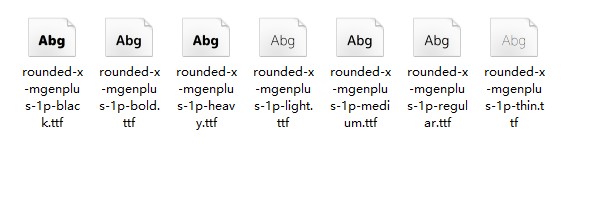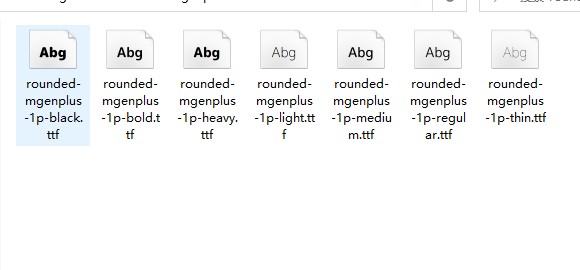
Rounded Mgen+ (日文名:ラウンデッド ムゲンプラス) 是以日本免费商用字体“M+OUTLINE FONTS”为基础进行圆角加工改造而成的字体,而本站之前介绍的源柔黑体(日文名:源柔ゴシック)也是以“M+OUTLINE FONTS”为基础进行扩展而成的字体。
Rounded Mgen+大约包含14000个字符以上,包括日文标准JIS第1-4水准,并且,也提供了几个版本的变化。分别是标准版、L、X。它们的区别在于圆角的圆润程度不同,L 圆角最小 (最尖),X 圆角最大 (最圆),而标准版则是介于两者之间。每个版本都有 7 种字重,3种字形样式 (包括等宽字体),大家可以根据喜好选择使用。
这款字体从本质上跟思源柔黑体并没有太大的区别,而且字符集是以日本的JIS水准为标准,所以对简体中文的支持度较差,对繁体中文支持度较好。虽然是免费商用的,但是本站也不推荐使用,因为对于我们国内的设计师,有另外一套也是基于思源思体而开发的圆形字体可以选择,那就是中国台湾设计师捣鼓出来的“源泉圆体”,对于简体和繁体的支持度比思源柔黑和这款Rounded Mgen+更好。